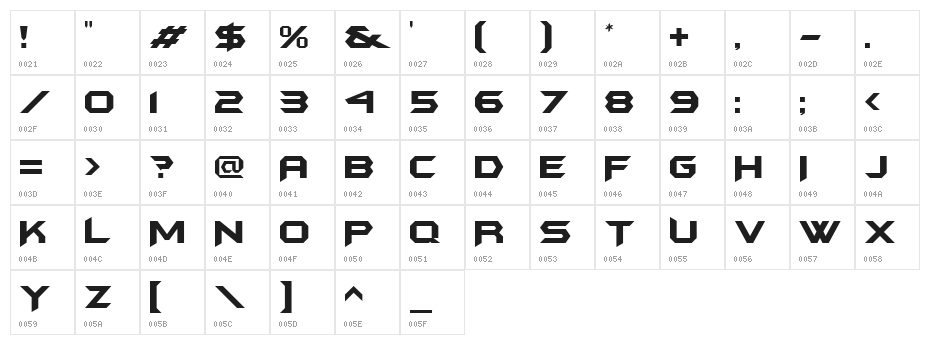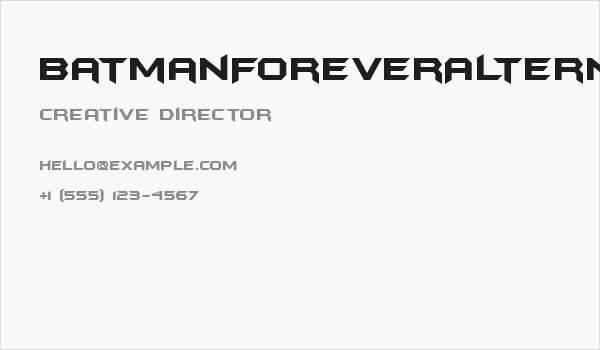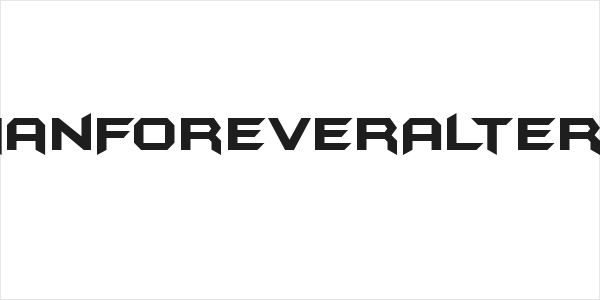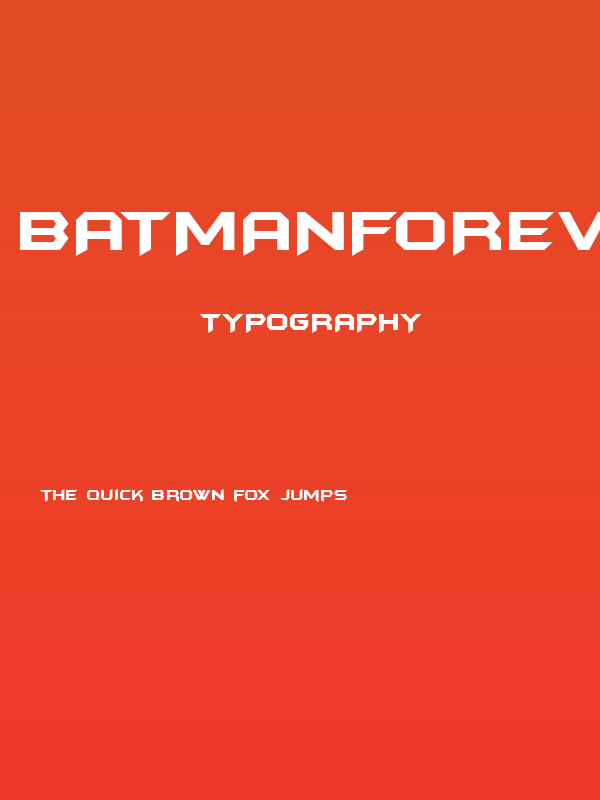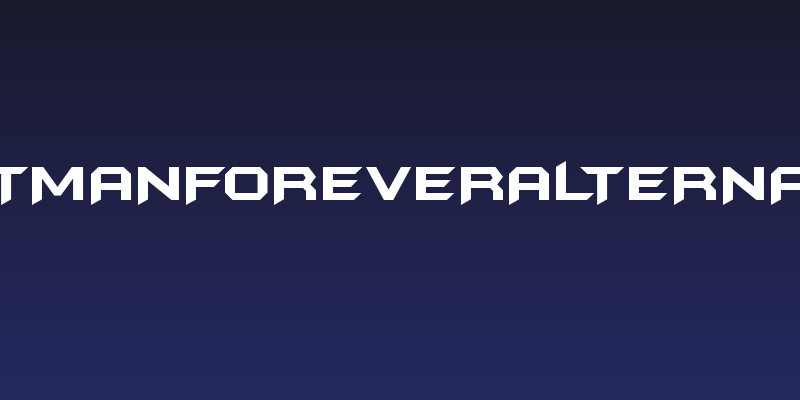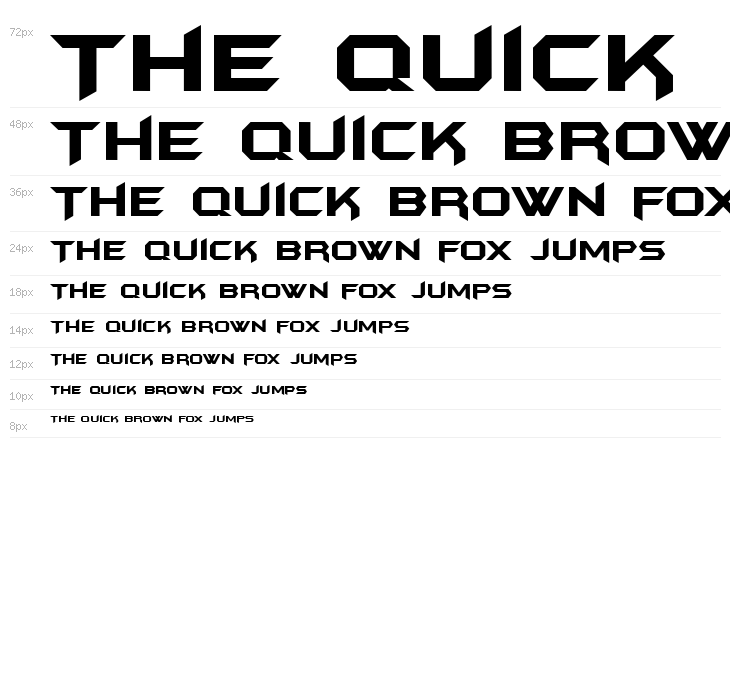
BatmanForeverAlternate Font
| Progetti proposti | Ideal for movie posters, video game titles, branding for tech companies, and any project needing a modern, edgy look. |